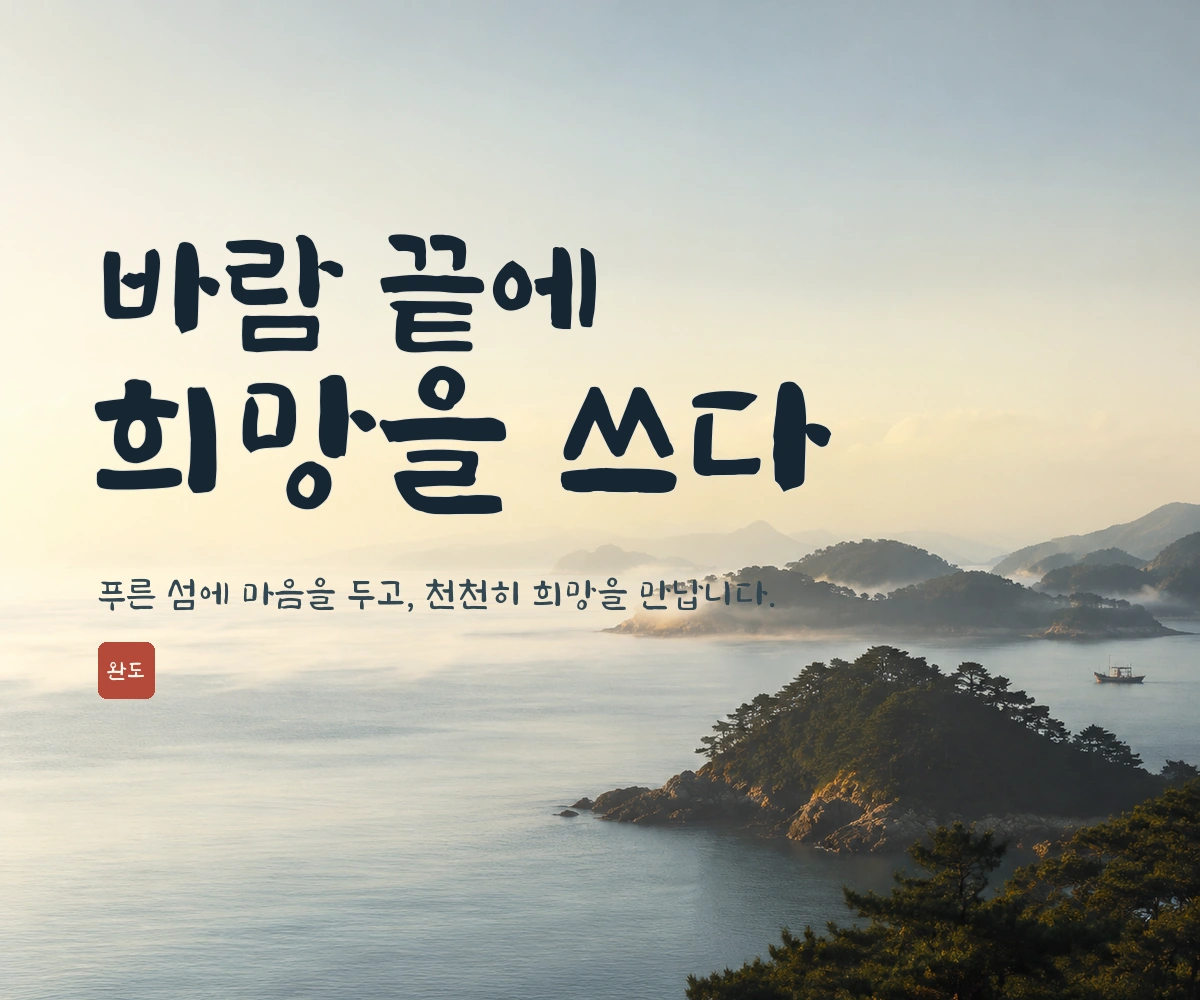
완도희망체 — 완도군에서 배포하는 무료 폰트입니다. 완도에서 유배 생활을 하며 동국진체를 완성한 명필 이광사의 필법을 담은 붓글씨 감성 제목용 서체
완도군이 2018년 1월에 공개한 전용 서체입니다. 민선 6기 군수 공약이던 원교 이광사 문화콘텐츠 자원화사업의 하나로 만들어졌습니다. 이광사는 조선의 이름난 명필로 완도 신지도에서 16년을 유배로 보내며 동국진체를 완성한 인물인데, 완도군은 그 필법을 글꼴에 담아 지역의 자산을 잇겠다고 밝히고 있습니다.
완도군이 설명하는 조형의 출발점은 이름 자체입니다. 완도의 완이 빙그레 웃을 완이라는 데서 실마리를 잡아, 주민들의 따뜻한 인심을 꽉 찬 구조에 담아냈다는 것입니다. 시각 중심을 가운데 두어 차분하고 안정적인 인상을 주고, 넓은 너비와 두꺼운 획이 더해져 여유롭고 너그러운 느낌을 낸다고 밝히고 있습니다. 파일에서 재어 보면 받침이 붙을 때 글자가 0.21em 더 내려가는 탈네모틀이라, 붓으로 쓴 듯한 흔들림이 남아 있습니다.